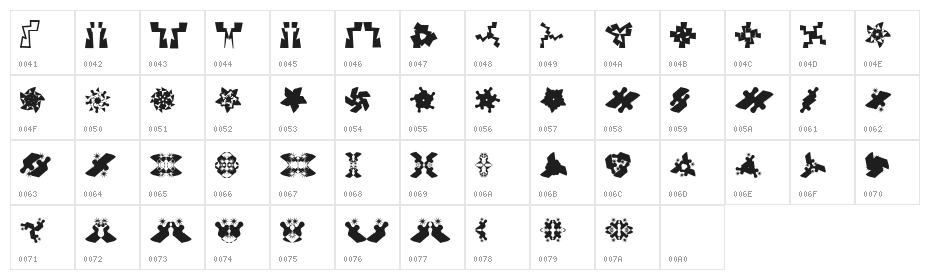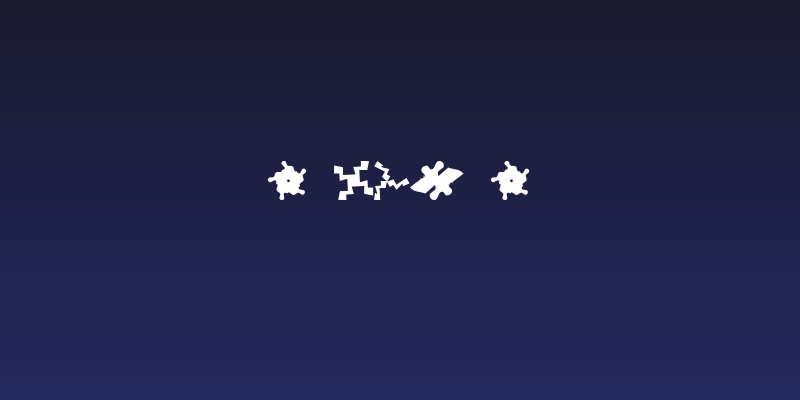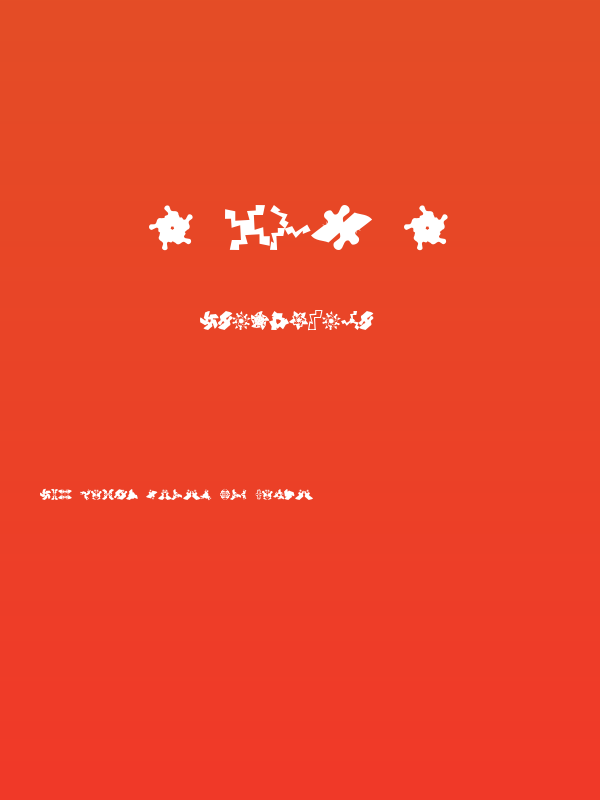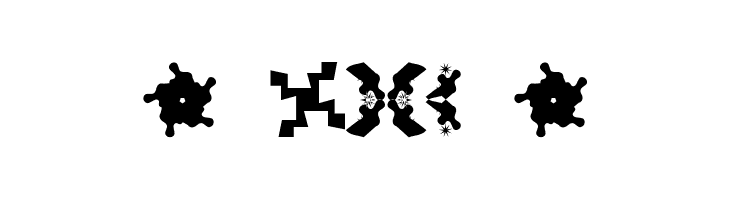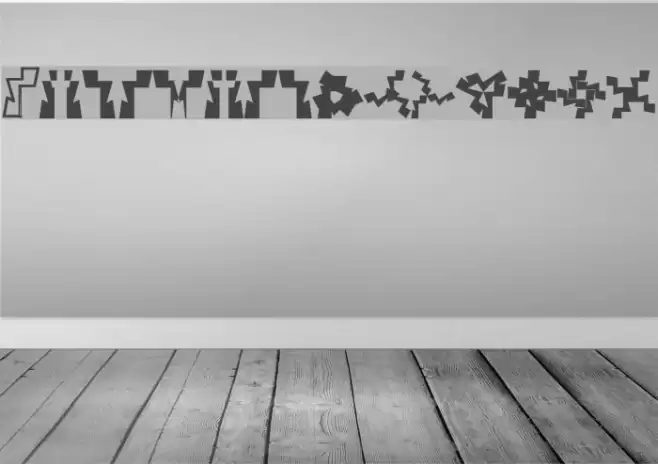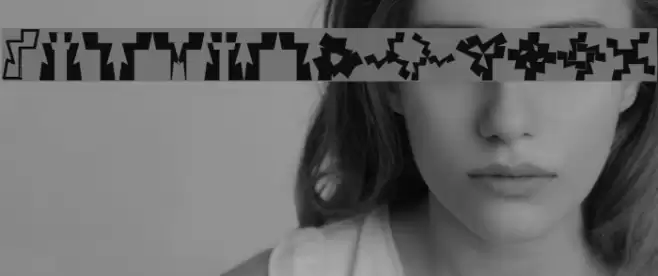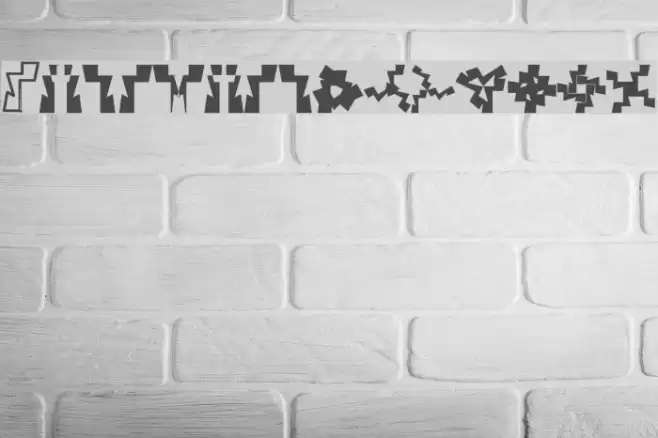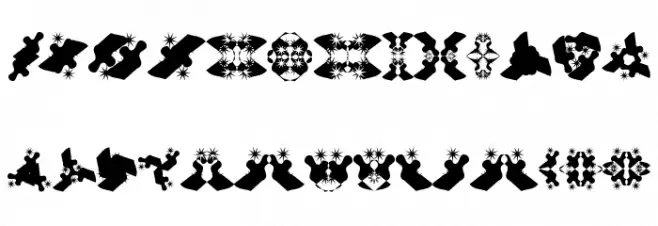
U-Mix-U Font
| Anwendungsfall | Logos, Posters, Artistic Designs |
| Vorgeschlagene Projekte | Ideal for artistic projects, album covers, posters, and any design requiring a bold, avant-garde statement. |